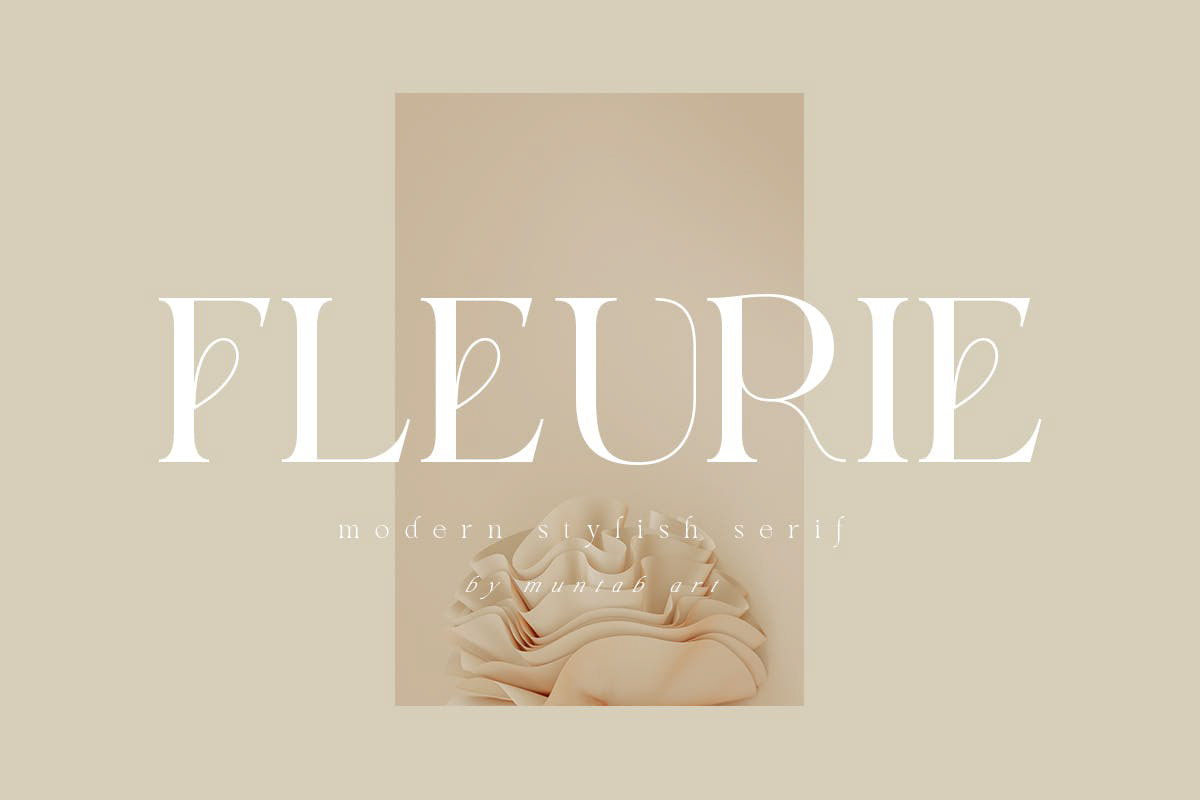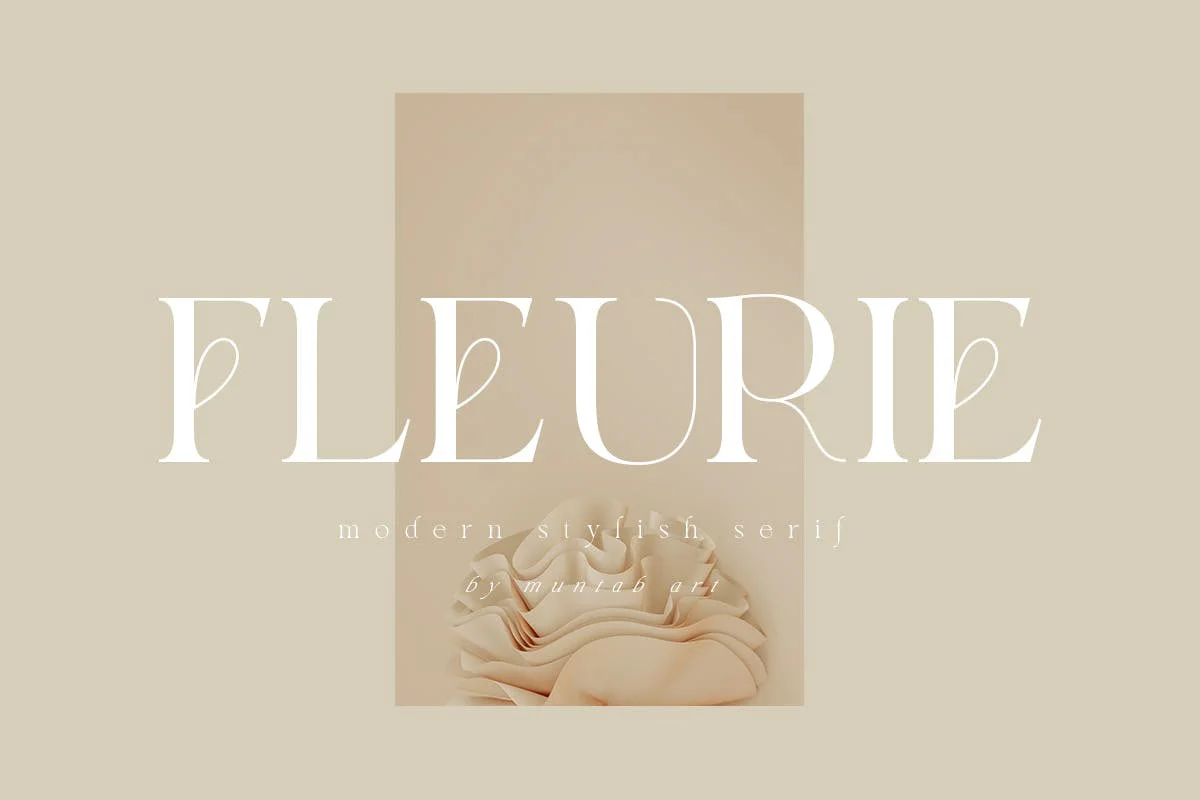
Название: Fleurie Font (2022)
Шрифт Fleurie включает прописные буквы, цифры, большой набор знаков препинания.
Шрифт Serif с современным стилем. Создан для плакатов, веб-дизайна, брендинга, иллюстраций, значков и некоторых других работ.